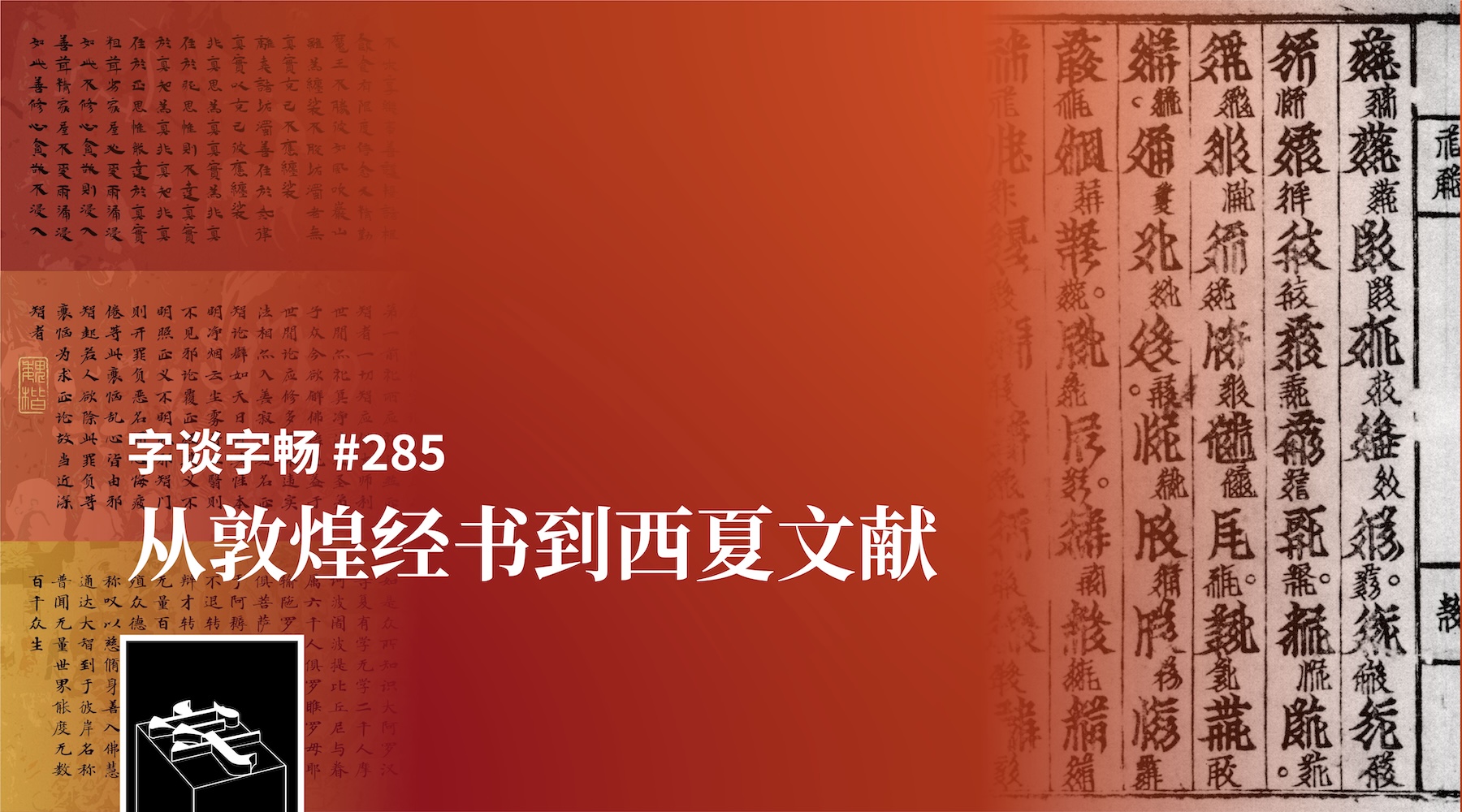
今天的嘉宾席依然邀请到两位 ATypI 2026 Stanford 的演讲者——刘翛瑀、杨翕丞——与我们分享各自在会议上的演讲主题,以及参会体验。
- “From manuscript to typeface: contemporary transformation of Dunhuang sutra scripts”,刘翛瑀在 ATypI 2026 Standford 的演讲
- “Remaking the Tangut script: new paradigms in designing digital typefaces for extinct writing systems”,杨翕丞在 ATypI 2026 Standford 的演讲
- 汉仪敦煌当代隶楷,高顺泽主创设计,汉仪字库出品
- 汉仪敦煌当代魏楷,韩公正、刘翛瑀主创设计,汉仪字库出品
- 汉仪敦煌当代唐楷,张延辉主创设计,汉仪字库出品
- 四角号码,汉字检字法之一
- 古今文字集成网站提供的西夏文字四角号码输入法